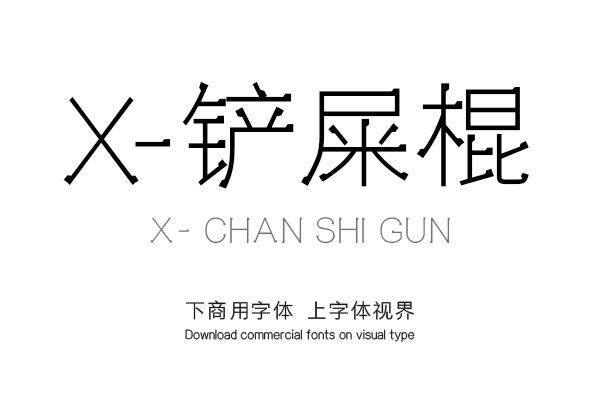
「X-铲屎棍」一款非常优秀好用的、艺术设计方面的中文创意字体
一款非常优秀好用的、艺术设计方面的中文创意字体,这款字体的笔画较细,字形方正,笔画下笔的地方都会有个特别的小装饰,非常有个性,该字体灵感来自于麻麻吸猫时铲屎的棍。
X-铲屎棍
《X-铲屎棍》笔画全部以坚硬的线条为形,弯曲的笔画多为折现或横竖交叉,空间上错落有致,在方正一律的感觉里制造了些新意。
X-铲屎棍